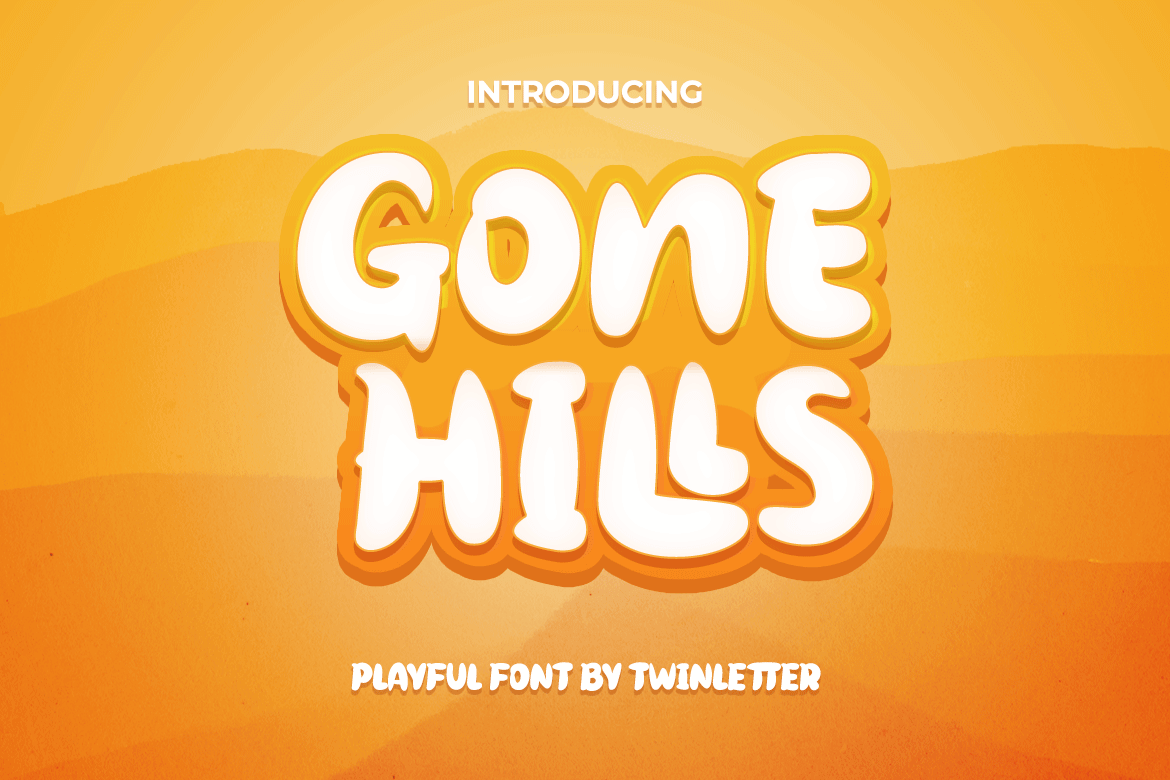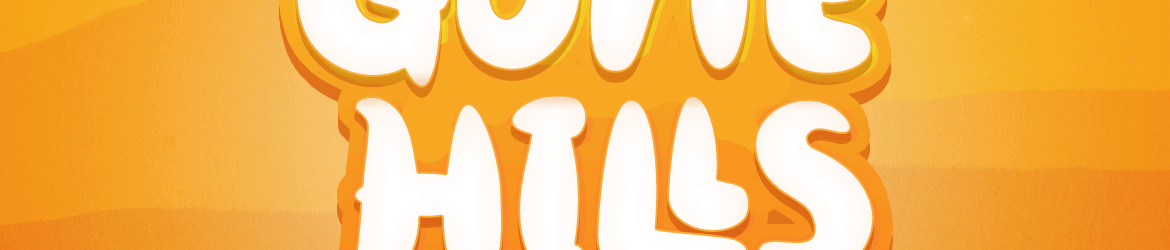
A Gone Hills Font é uma tipografia tipo display perfeitamente adequada para projetos criativos variados. Seu uso garantirá que seus trabalhos sejam atraentes e naturais aos olhos de quem os observa, elevando a qualidade das suas gráficas. Esta fonte carrega um toque leve e divertido, ideal para criar design visual que chama atenção e transmite uma mensagem positiva e deslumbrante. Seja ela usada em cartazes impressionantes, logotipos memoráveis ou qualquer outro projeto gráfico, a Gone Hills Font estará sempre por trás de um resultado irresistivelmente atrativo.